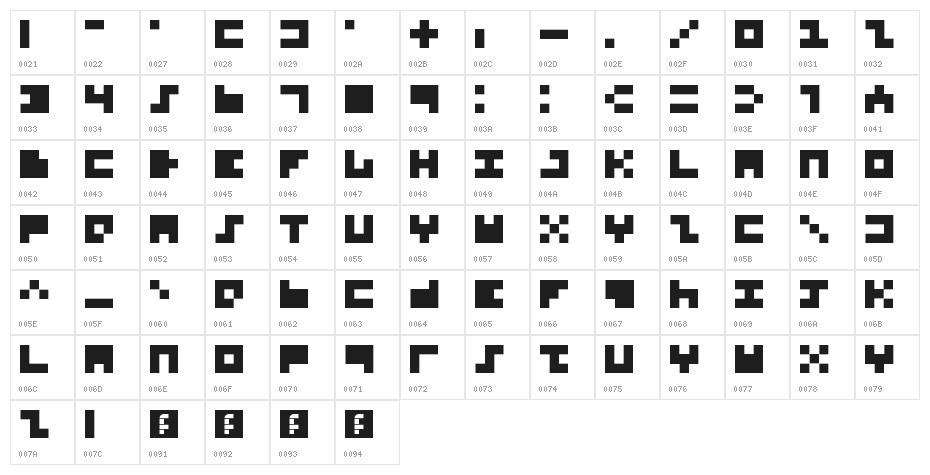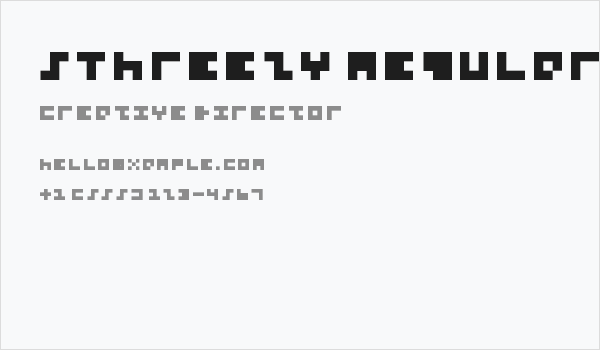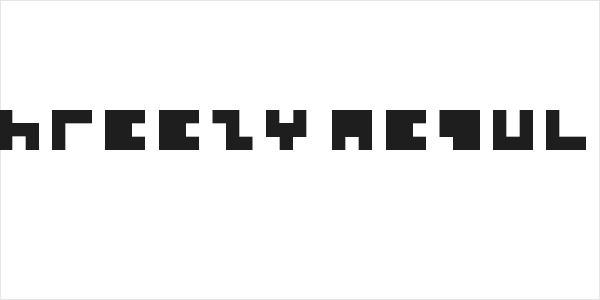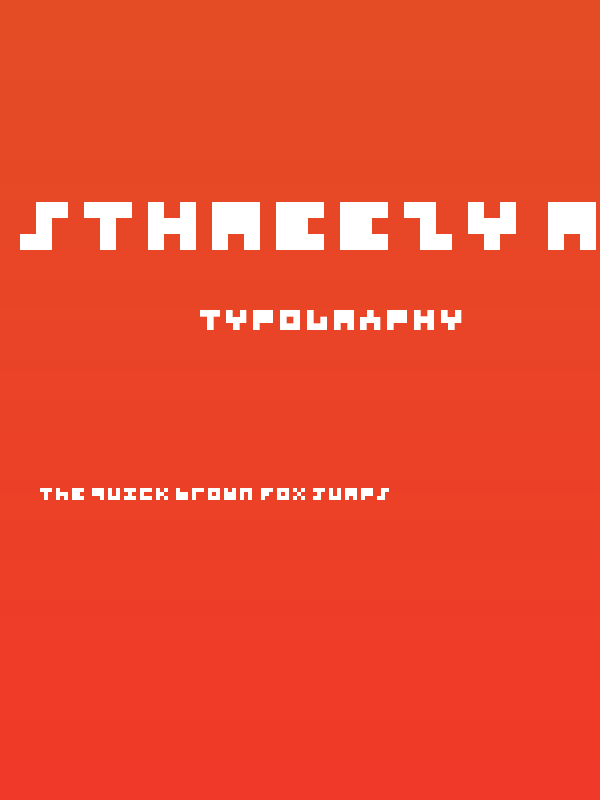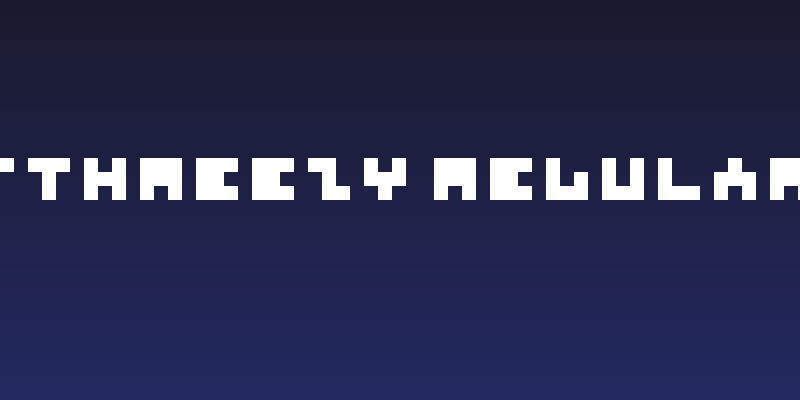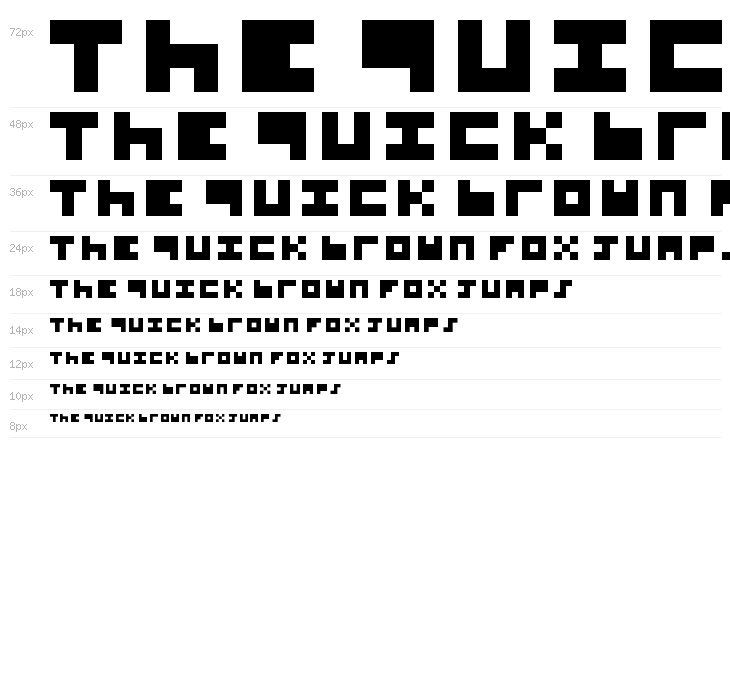
5Threezy Regular Font
✎ Pixel
| Anwendungsfall | Logos, Headlines, Posters |
| Vorgeschlagene Projekte | Ideal for video game design, digital art projects, tech-themed posters, or any creative work requiring a retro digital feel. |